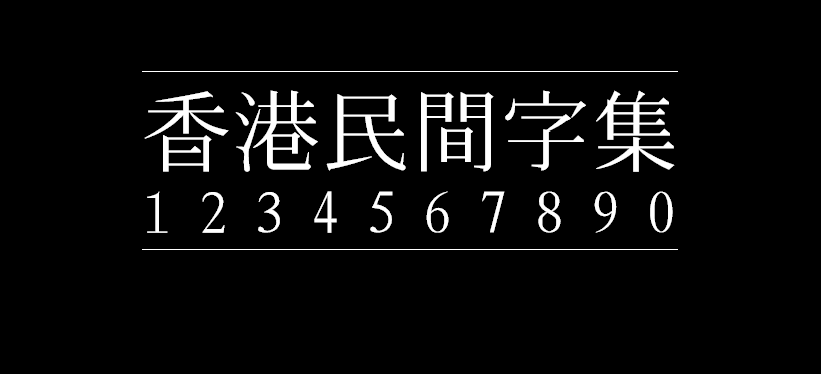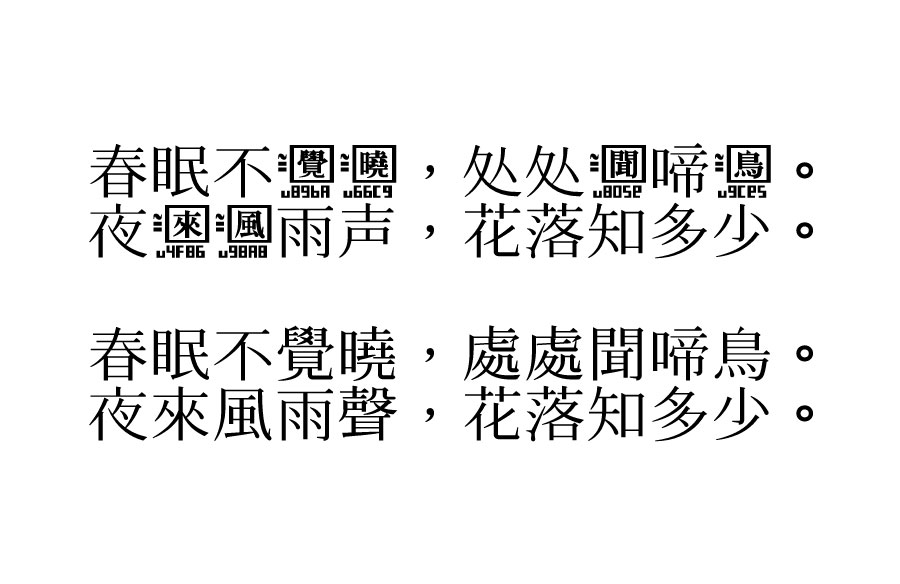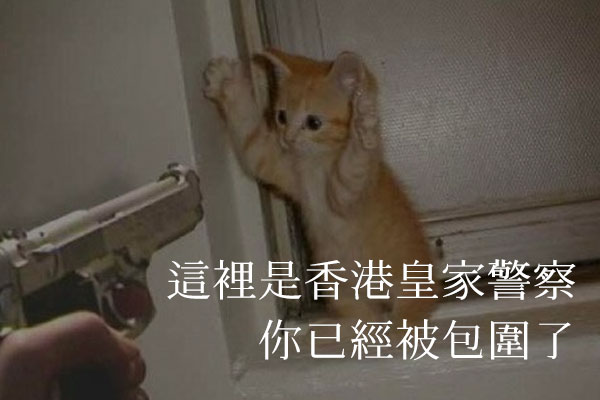
香港民间字集
香港民间字集(Hong Kong Character Set 香港民間字集 傳承字形版)一种衬线字体,根据@SyaoranHinata概述的拼字法支持传统拼字法,选择的传统拼字法是比较适合现代甲骨文,青铜铭文和小海豹词源研究的拼字法。 该字体繁体字符比较全,简体相对少一些。该字体遵循SIL Open Font License协议,可免费商用。